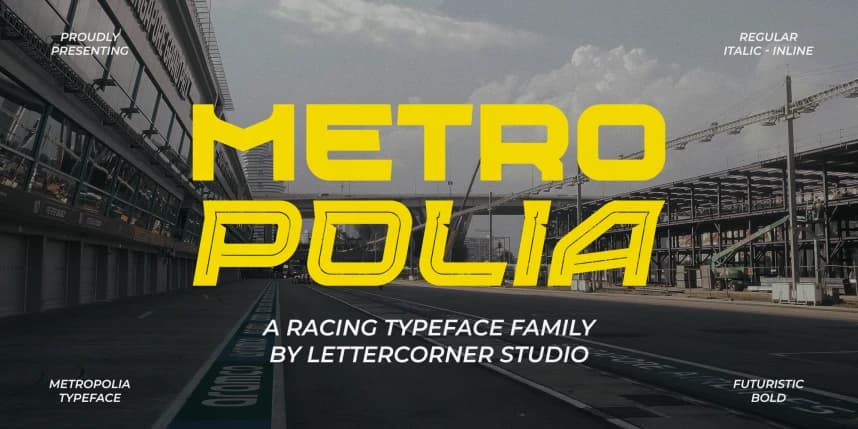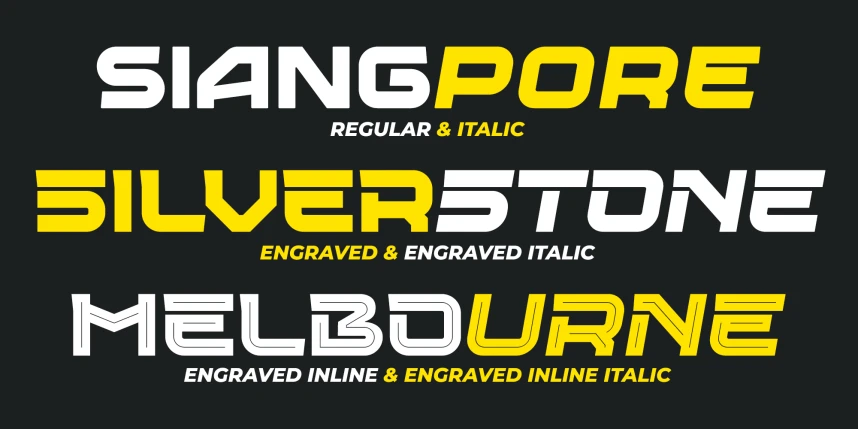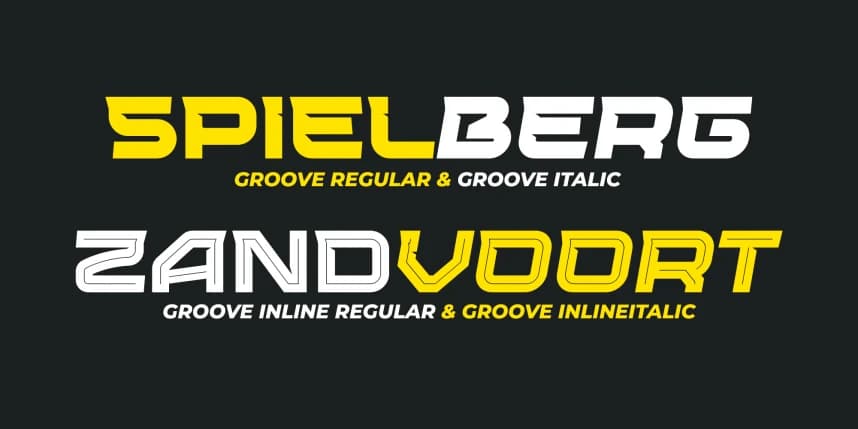
METROPOLIA - RACING TYPEFACE, hızı, hassasiyeti ve fütüristik bir hava sunmak için tasarlanmış cesur bir yarış tipografisidir. Keskin açılar, uzatılmış harf biçimleri ve dinamik yapısıyla yüksek performanslı motor sporlarının adrenalinini ve hareketini yakalar.
METROPOLIA - RACING TYPEFACE, hız, hassasiyet ve geleceğe yönelik bir keskinlik sunmak için tasarlanmış cesur bir yarış tipi yazı karakteridir. Keskin açılarının, uzatılmış harf formlarının ve dinamik yapısının etkisiyle, yüksek performanslı motor sporlarının adrenalinini ve hareketini yakalar.